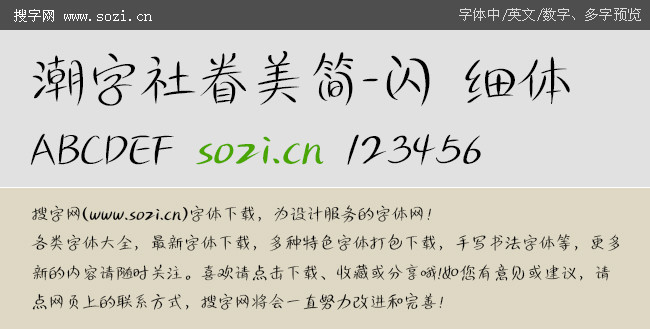
潮字社眷美簡-閃 細體
搜字網(wǎng)提供一款潮字社眷美簡-閃 細體中文字體下載,潮字社眷美體是一款線條優(yōu)美圓潤的藝術(shù)字體,風格比一般的字體更有特色,連貫字跡顯得干練而不凌亂,清新簡明,具有很好的視覺感,適合應(yīng)用于藝術(shù)設(shè)計、平面宣傳設(shè)計、網(wǎng)頁設(shè)計等領(lǐng)域等應(yīng)用。(本字體為個人非商用版,商用請聯(lián)系作者購買授權(quán))